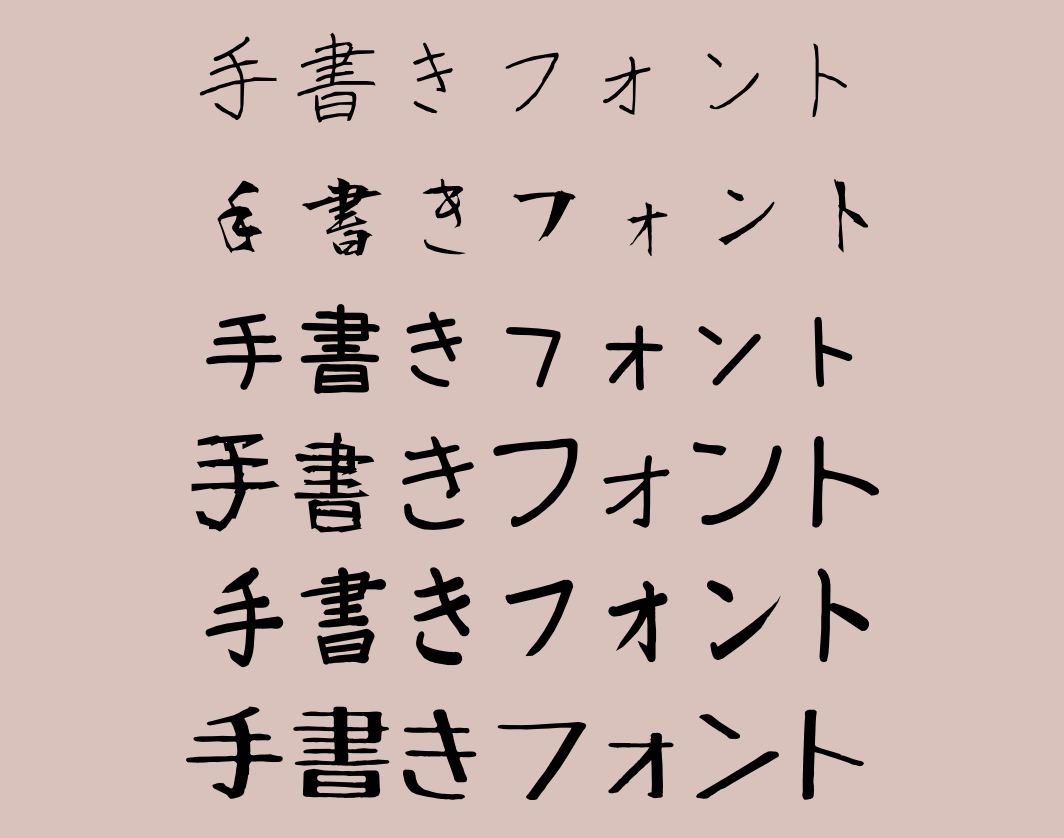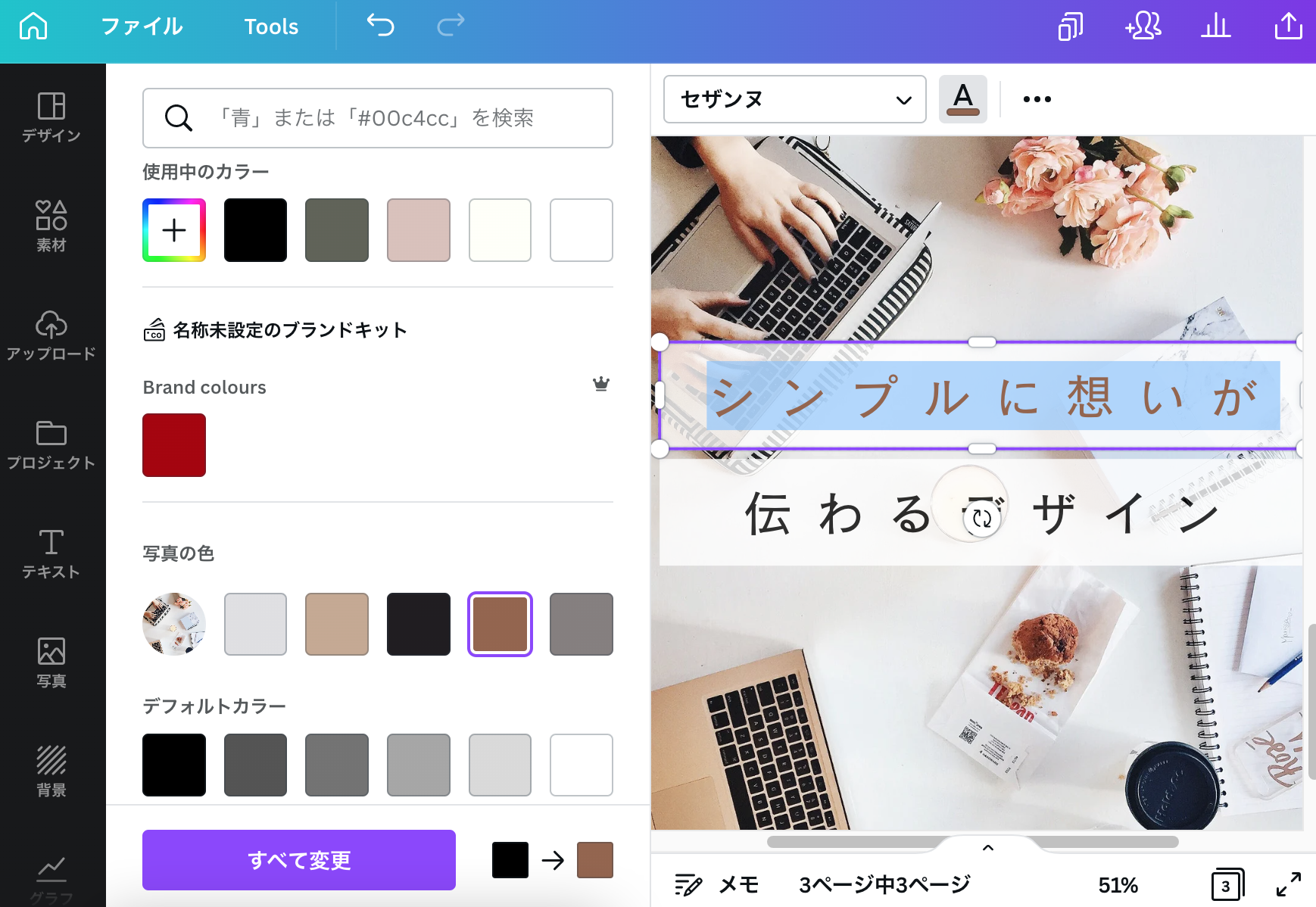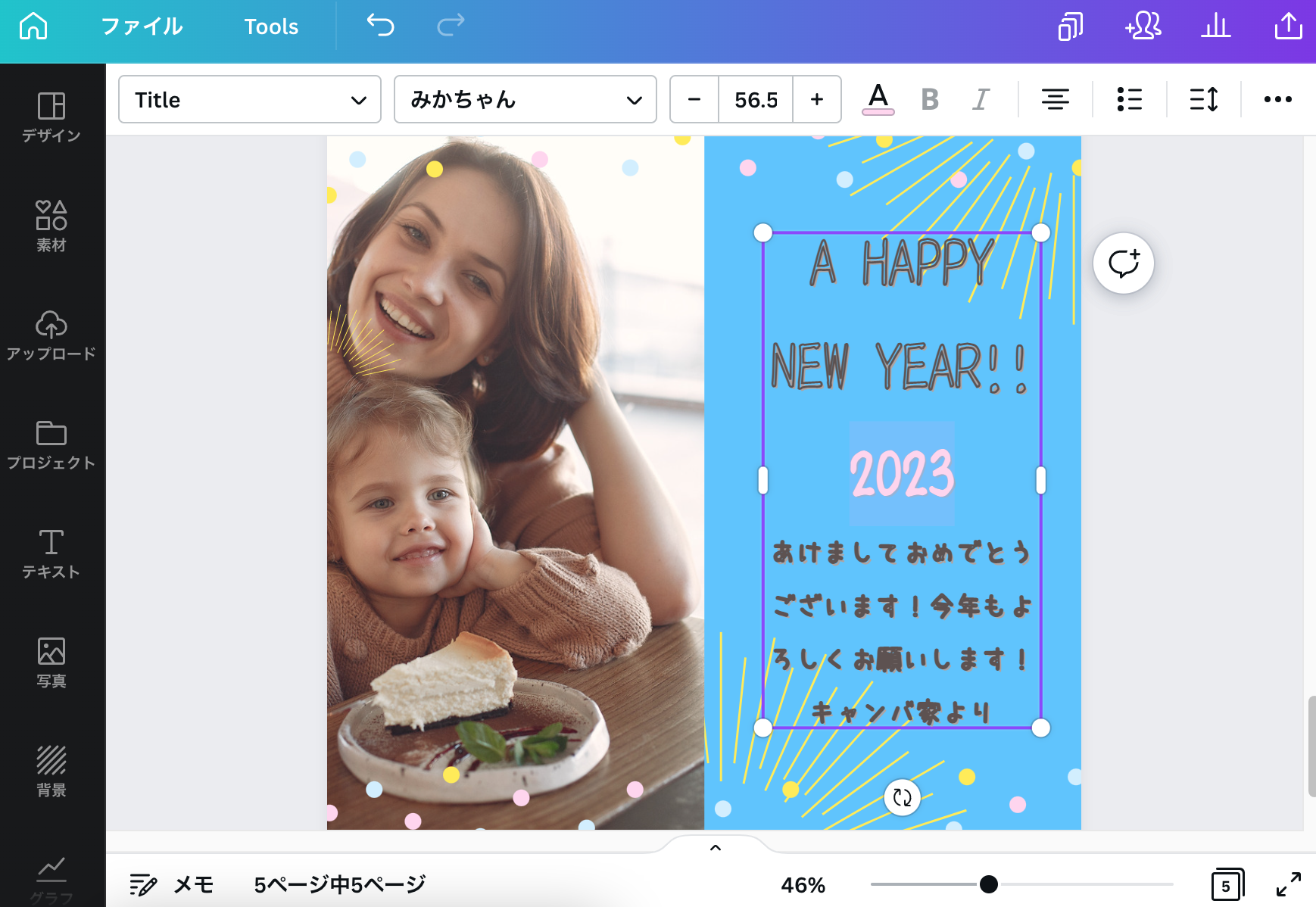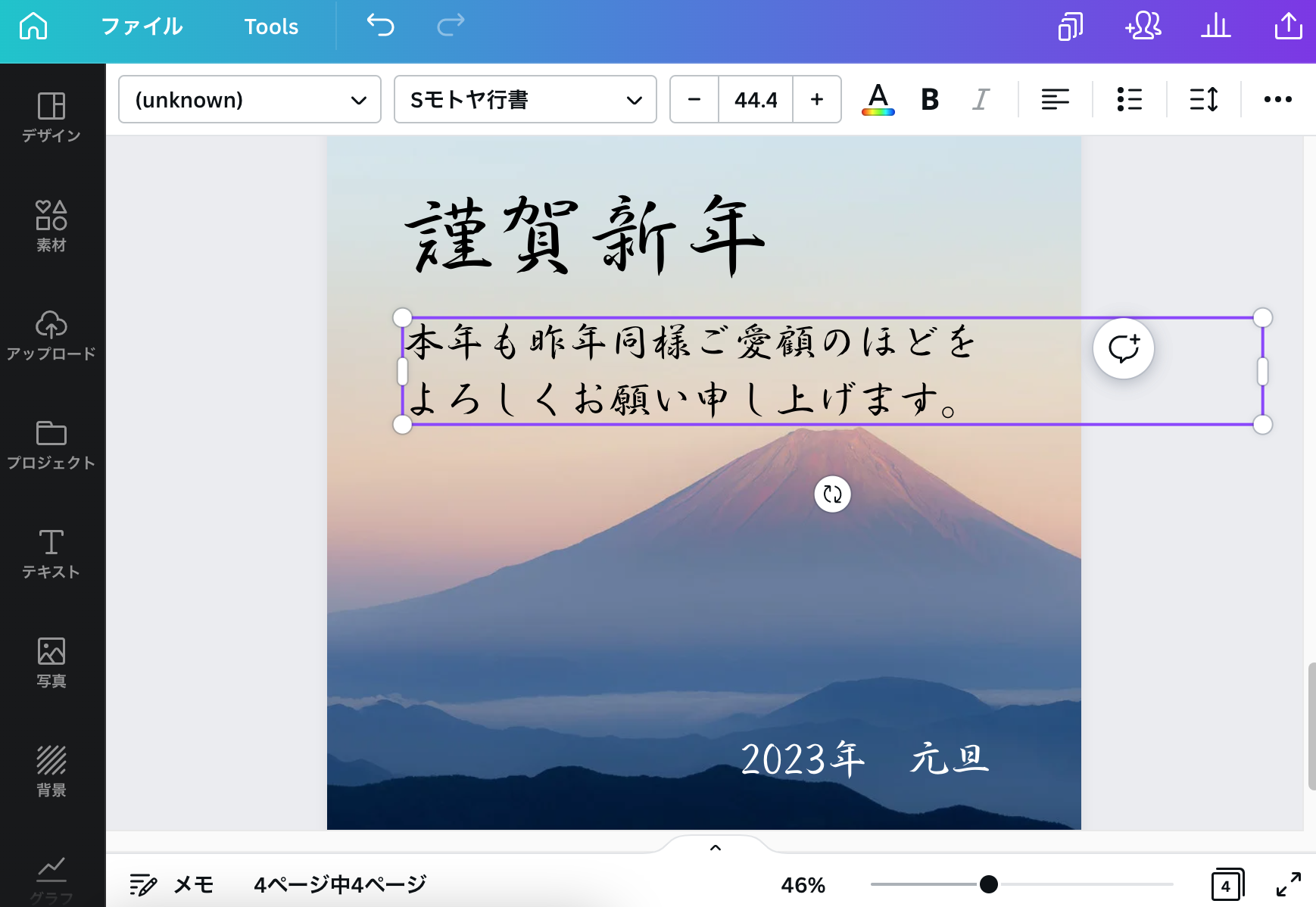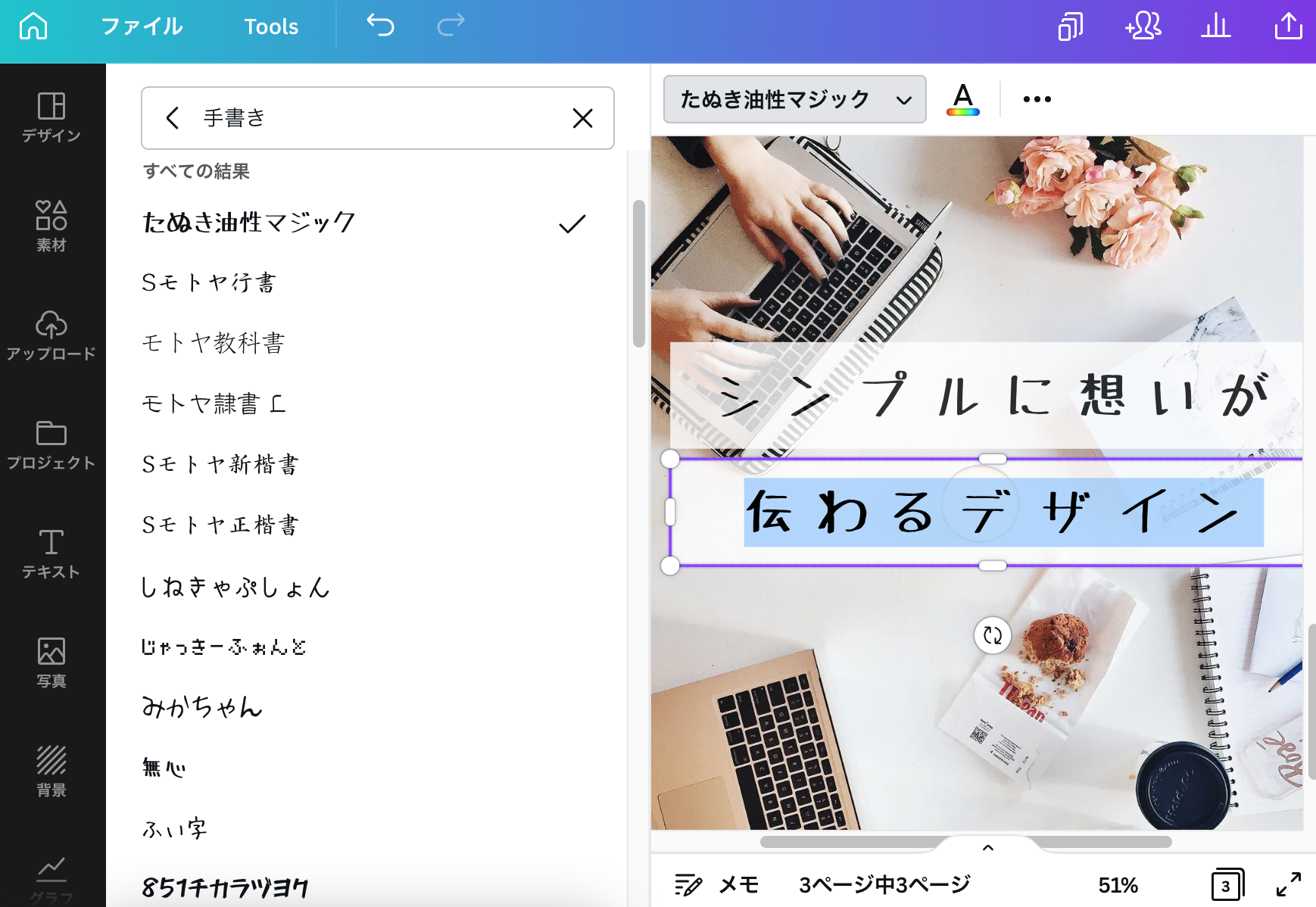
手書きフォントでデザインを作成
手書きフォントでデザインを作成しよう!
多種多様の手書きフォントをお使いいただけます
Canvaの手書きフォントは増え続けています。どんなデザインにも使用できるように、さまざまな種類で手書きフォントを取り揃えています。なかには、子どもフォント、筆フォント、極細フォントの手書きフォントがあります。マジックで書いたようなデザインやお習字デザインなど、多種多様なフォントが使えるのでデザインするのも楽しくなるはず!
手書きフォントの色を編集する方法
手書きフォントを選択し、文字を入力します。テキストの色も、もちろん編集できます。上部メニューから[A]のアイコンを押します。左パネルにカラーパレットが表示されます。デフォルトカラーのほかに、「写真の色」が自動的にまとめられている機能もあります。おすすめ色を推奨してくれるので、迷わずにデザインに合ったものを選べます!サイズの変更も1単位から変更可能です。
手書きフォントにエフェクトを加えて文字を引き立たたせる
手書きフォントには、テキスト編集機能の「エフェクト」がお使いいただけます。文字にインパクトを足したり、目立たせることができるのでデザイン作成にはおすすめです。例えば、インスタ投稿をデザインするとき、文字を背景と区別させることで、見やすく効果的なデザインになります。追加した手書きフォントを選択し、エフェクトから「背景」を追加しましょう。背景に色を加えて透明度も調整すると、あっという間におしゃれな投稿が完成!
手書きフォントで文字を上品にすることができます
手書きフォントで文字を一段と美しく、上品にすることも可能です。手書きで毛筆フォント、教科書フォントがおすすめです。[テキスト]の検索バーに「筆」と入力すると、あらゆる筆フォントが表示されます。万年筆や掛け軸にあるようなフォントが見つかります。スタイリッシュでありながらフォーマルなフォントを追加して、メッセージに上品さを加えてみましょう。
手書きフォントで年賀状をデザイン
手書きフォントを使えば、温かみのある雰囲気を足すことができるため、年賀状デザインにもおすすめです。「〇〇家より」と家族からのメッセージを書きたいときに手書きフォントを使用してみてください。個性的にしてみたり、可愛らしくしてみたり、直筆で書いたような上品で美しい雰囲気にしてみることもできます。
手書きフォントの探し方とデザインに使用する方法